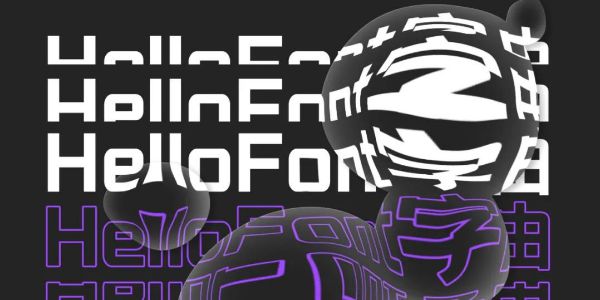
两个图形或两个线条之间的混合效果
效果案例
这篇是AI混合工具升级篇
利用混合工具里的替换混合轴实现立体背景
利用混合工具里的替换混合轴
实现618立体字海报
首先替换混合轴在这里
菜单对象-混合-替换混合轴
怎么用呢?先打个字母描个边,执行混合效果在单独画一条路径,框选中字和路径。
文字-绕路径
执行菜单对象-混合-替换混合轴。字会绕着路径形这就是混合轴的运用!实现各种环绕效果。已画好路径还能进行路径微调。
放大缩小文字
还可以进行文字放大缩小以及文字修改
修改颜色
还能修改文字颜色,纯色或渐变色按你喜好来,又能进行混合选项的在次修改。
不仅是文字
图形也可以用替换混合轴各种变形
图形-绕路径
首先选一张图形勾出路径
然后开工
在调整下路径位置让效果更好
反向混合轴在这里
菜单对象-混合-反向混合轴
反向混合轴在已执行过替换混合轴效果后使用,使已替换的混合轴效果进行位置调换。
反向堆叠在这里
菜单对象-混合-反向堆叠
反向堆叠,是让替换混合轴效果更立体。
马上用学到的做案例
先在AI里完成基础形状制作
在导入PS里进行海报设计
来看下完整版
在AI中勾勒出立体字形状,在画三个渐变圆进行混合效果这里的混合步数建议200以上数值,选中渐变色条和轮廓,执行对象菜单-混合-替换混合轴,这时多彩立体字效果就完成。
形状完成后接下来618字重复一样操作
画好的形状带入PS里在进行海报设计
最后看下完整版